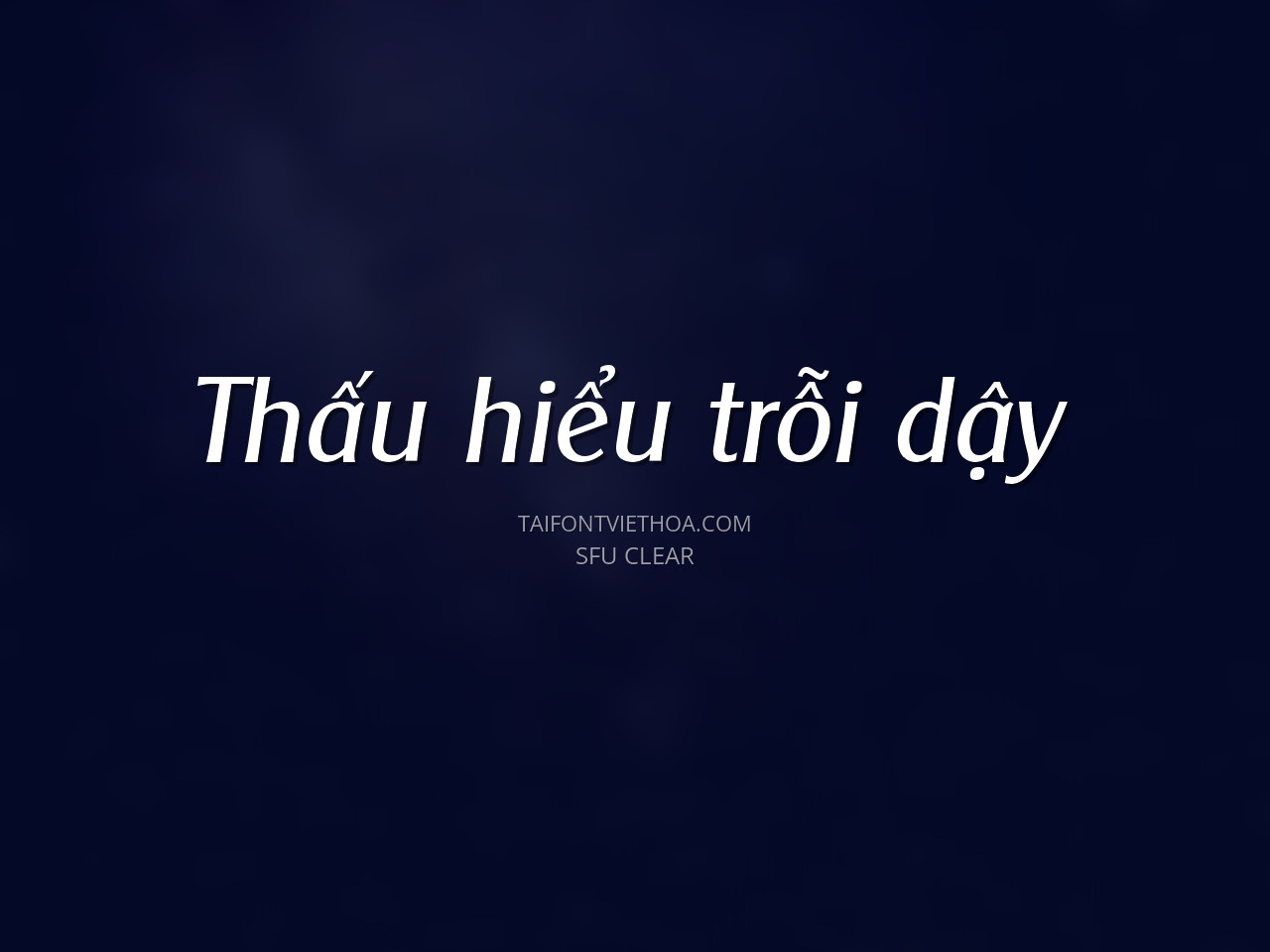
Font việt hóa SFU Clear
Giới thiệu về font SFU Clear – Kiểu chữ hiện đại với khả năng hiển thị tối ưu
SFU Clear là phiên bản Việt hóa của font Clear – một kiểu chữ sans-serif hiện đại được thiết kế với mục tiêu tối ưu khả năng đọc trên cả màn hình kỹ thuật số và bản in. Font này không quá cầu kỳ trong phong cách, nhưng lại được ưa chuộng bởi sự đơn giản, cân đối và hiệu quả thị giác. Clear thường xuất hiện trong các thiết kế liên quan đến công nghệ, giao diện người dùng (UI), hệ thống bảng biểu, và các tài liệu doanh nghiệp cần sự rõ ràng, dễ đọc.
Phiên bản SFU Clear đã được Việt hóa đầy đủ, hỗ trợ toàn bộ dấu tiếng Việt cùng hơn 90 ngôn ngữ khác. Taifontviethoa.comđã chọn lọc và chia sẻ font này trong bộ sưu tập những kiểu chữ sans-serif thân thiện, dễ sử dụng nhằm phục vụ cộng đồng thiết kế tại Việt Nam – đặc biệt trong các ứng dụng thực tế như website, mobile app, ấn phẩm thương hiệu và hệ thống văn bản kỹ thuật.
Thiết kế tối giản – Hiệu quả cao và ứng dụng rộng rãi
SFU Clear sở hữu cấu trúc sans-serif không chân, với tỷ lệ chữ cân bằng và đường nét rõ ràng. Các ký tự được thiết kế gọn gàng, có độ mở lớn và khoảng cách hợp lý, giúp văn bản dễ tiếp cận và đọc nhanh trên cả màn hình lẫn in ấn. Phong cách thiết kế này mang lại cảm giác chuyên nghiệp, hiện đại mà không đánh mất tính thân thiện thị giác.
Ứng dụng lý tưởng: hệ thống nhận diện thương hiệu, slide thuyết trình, giao diện app/mobile, website doanh nghiệp, bao bì sản phẩm công nghệ và biểu mẫu hành chính. Ngành nghề phù hợp: công nghệ, giáo dục, startup, tài chính, hành chính – văn phòng, bất động sản và thương mại điện tử.